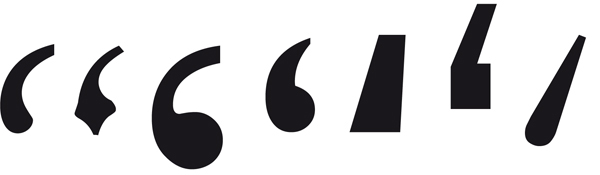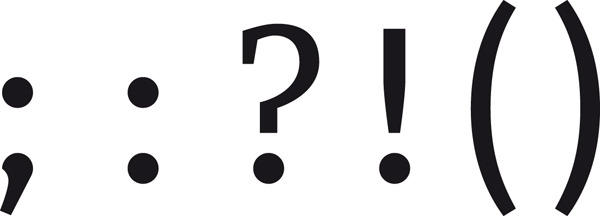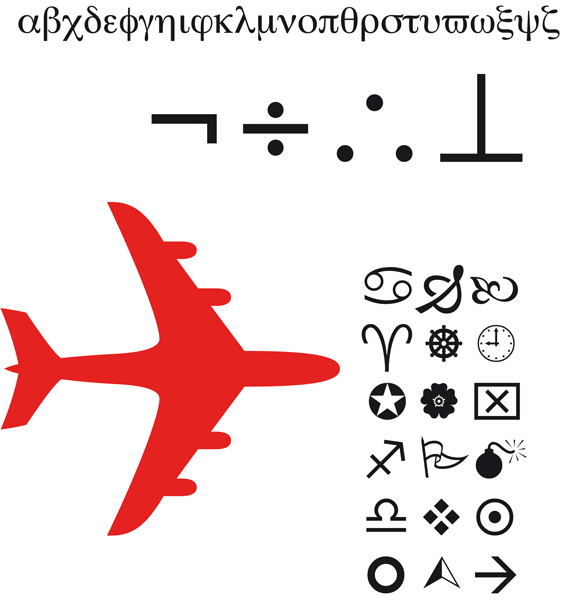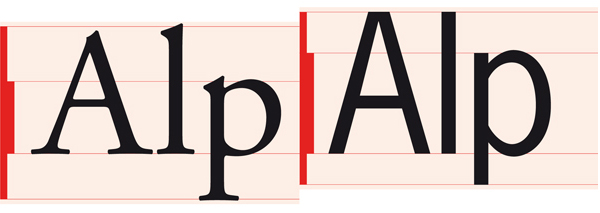
La familia tipográfica bajo lupa
En los diferentes países y lenguas han aparecido a lo largo del tiempo diversos nombres para designar las formas y partes de un tipo de letra. En la época de los ordenadores a todas ellas se ha sumado una terminología fundamentalmente inglesa que viene a acentuar el caos conceptual. ¿Cómo se llama ahora: cursiva, oblicua o itálica? ¿Redonda o regular? La simplificación es imprescindible, pero todavía no se divisa. En este libro, al menos, se impone la claridad conceptual, por lo que se abordan a continuación algunas definiciones de los conceptos empleados.
Un grupo tipográfico comprende tipos de letra que presentan ciertas semejanzas, por ejemplo los manuscritos. Una familia tipográfica es el conjunto de las formas en que se presenta un tipo de letra y se designa con un nombre (con diversos modificadores), por ejemplo Rockwell o Helvetica. En este libro se designa como fuente una variante de un tipo de letra, como por ejemplo las diferencias de resalte (negrita o cursiva), de ancho (condensed o extended), de ángulo (oblicua) o incluso de forma (cursiva u oblicua), o la combinación de algunos de estos parámetros, como en el caso de la Helvetica 23 Ultra Light Extende Oblique. La versión estándar, normal o redonda de un tipo de letra se llama a menudo 'romana'. Por tanto, un tipo de letra puede contener varias fuentes. Cuando compramos una fuente para el ordenador, en realidad adquirimos el ojo de una letra. Con frecuencia se adquieren en grupos de cuatro, como por ejemplo redonda, cursiva, negrita y negrita cursiva.
La letra Serifa de Linotype con las fuentes disponibles.
Las 26 letras del alfabeto solo son la base de los signos que forman una fuente. Una fuente sin cifras, signos de puntuación, signos especiales y signos diacríticos no está completa. Además, cada lengua cuenta con sus propios signos de puntuación y sus combinaciones de letras (ligaduras), que el diseñador incorpora en determinadas fuentes.
Las MAYÚSCULAS y las minúsculas
En las clases de escritura la letra mayúscula se conoce también con el nombre de versal. Las mayúsculas o versales derivan de las inscripciones romanas esculpidas en piedra y en muchos casos todavía mantienen su carácter geométrico, apto para ser cincelado. Las minúsculas son el resultado de la evolución de la letra manuscrita.
La letra Trajan diseñada por Carol Twombly para Adobe se inspira en las inscripciones romanas de la columna de Trajano en Roma (erigida en 113 d. C.).
La letra Blado fue diseñada en 1923 por Stanley Morison a partir de una cursiva de 1526 de Ludovico degli Arrighi. Aunque era un tipo de letra independiente, se ha usado frecuentemente en combinación con la Poliphilus (arriba) diseñada por Morison para Monotype. Las de Arrighi pasan por ser las primeras cursivas concebidas para la imprenta.
Variantes
Se ha extendido la creencia de que la versión cursiva o bastardilla de una letra aparecía siempre de forma paralela a la fuente principal. En absoluto; la cursiva o bastardilla apareció a comienzos del siglo XVI y tenía su origen en la caligrafía humanística italiana de la época. Inicialmente se utilizó como tipo para textos y se atenía a una caligrafía que ahorraba espacio.
La Stempel Garamond Roman reproduce los caracteres diseñados por Claude Garamond para una edición de la Hypnerotomachia Poliphili (El sueño de Polífilo) impresa en París por Jacques Kerver en 1546, que a su vez se inspiraban en la romana grabada por Francesco Griffo unos 50 años antes para el impresor Aldo Manucio.
Las versalitas
Son las versiones pequeñas de las versales; no son meras mayúsculas reducidas, sino más bajas y específicamente diseñadas, susceptibles de encontrarse en una familia tipográfica como los tipos de letra denominados expert, sc o caps. Las VERSALITAS son generalmente algo más altas que el ojo medio (altura de la x) y su grosor está adaptado. La altura de la x es la altura de una x minúscula.
La Syntax fue diseñada por Hans Eduard Meier y publicada por primera vez por Linotype en 1968. Fue la primera letra sin remates que se produjo tanto para tipos de plomo como para fotocomposición. A finales de la década de 1990 se llevó a cabo una amplia revisión del diseño, añadiendo algunas fuentes, entre ellas las versalitas (arriba, izquierda, segunda línea). Las versalitas aparecieron por primera vez en torno al año 1525. 500 años después se integraron formalmente en la familia gráfica, al igual que las cursivas.
Las ligaduras, los diptongos y los logotipos
Las ligaduras eran combinaciones de caracteres cuyo origen se encuentra en los problemas que presentaban ciertas letras en la composición con plomo; la f, por ejemplo, se extendía tanto por su pestaña sobresaliente que alcanzaba el ascendente del carácter siguiente o el punto de la i. En ciertos logotipos se pasa por alto el hecho de que constan de dos signos; son los casos del alemán ß y del signo &, ambas combinaciones tienen su origen en ligaduras. Los diptongos son conjuntos de dos vocales diferentes (en español se forman con la combinación de i e u con otra vocal) que se pronuncian en una sola sílaba. En el caso del francés algunos diptongos dan lugar a una ligadura, como en œil ('ojo').
En el signo & de la Demos Italic y la Galliard Italic todavía se distinguen perfectamente las dos letras del latín (et). En la alega de (derecha) la combinación inicial es menos evidente. Aunque en general esta combinación se encuentra en logotipos, las versiones de Demos y Galliard pueden también considerarse como ligaduras.
3.3 Pictogramas
Estos signos exigen al espectador más fantasía que los símbolos. Los pictogramas (del latín pictum, ‘pintado’, y el griego graphein, ‘escribir’) son imágenes estilizadas susceptibles de transmitir una indicación o una información. Son casi siempre decorativos y llevan la firma de sus creadores. Se conocen también con el nombre de fuentes clip art.
Zeitguys One (Diseñado en 1994 por Eric Donelan y Bob Aufuldisch para Emigre.)